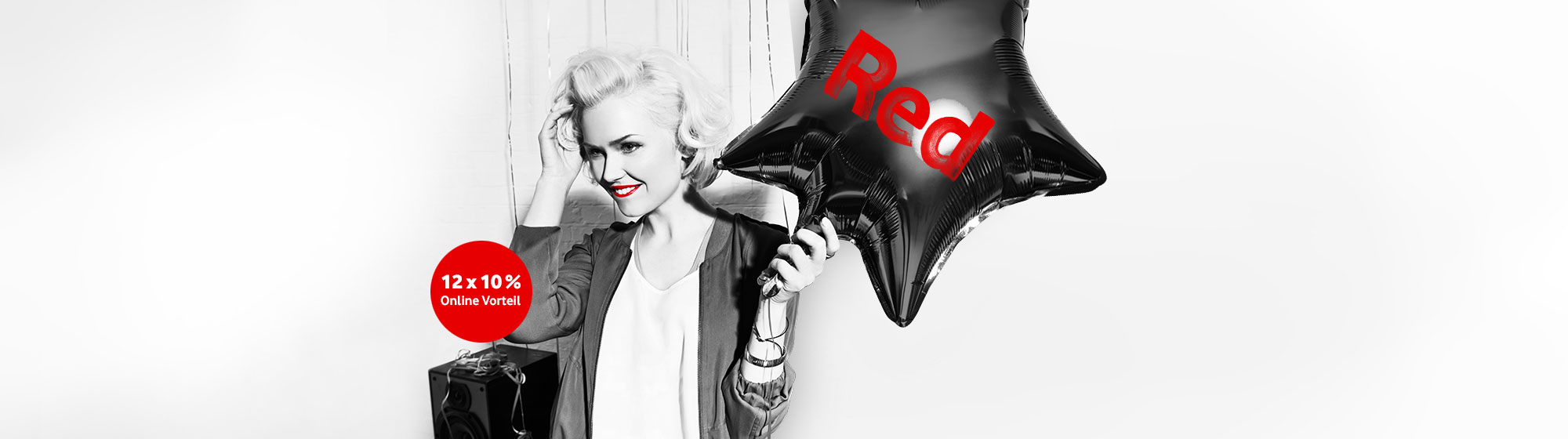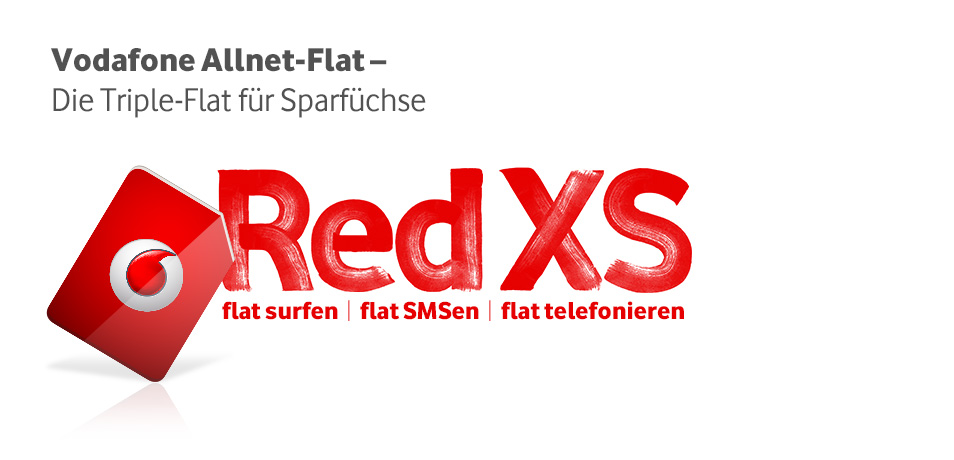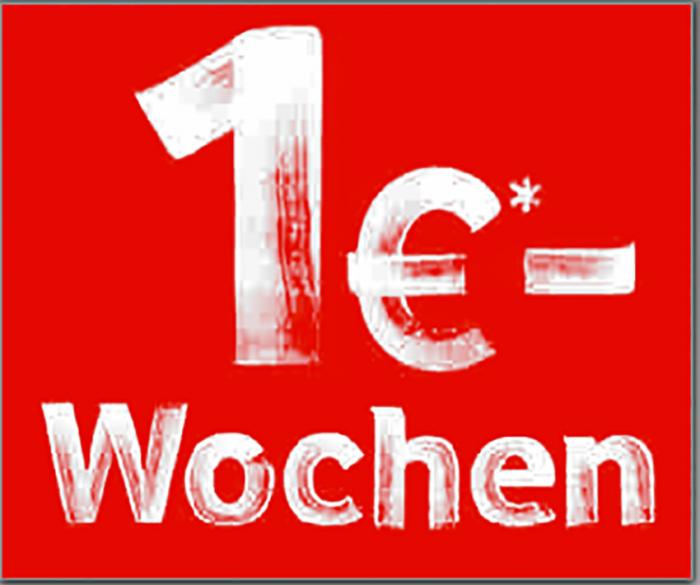
Wie heißt die Schrift von dieser Werbeanzeige?
gerade ist mir eine Handmade-Schriftart einer Webanzeige ins Auge gesprungen. Wisst ihr wie diese Schrift heißt?
vermutlich ist es einfacher, wenn Du die Anzeige mal verlinkst.
Aus dem Bauch raus, würde ich allerdings auf "handgemacht" tippen – zumindest der Kreidemarker-Effekt.
Das müsste aus der Vodafone-Werbung sein, also eher ein Font.
Ja, nachdem das Design nicht als Fließtext verwendet wird, könnten auch die Einzellogos RedXS usw. im Photoshop aus der Vodofone-Schrift erstellt worden sein. Klingt plausibel.
Dass es ein Font ist der auf der Hausschrift basiert ist wirklich gut möglich. Danke für die Info. Ggf. suche ich mal nach einer ähnlichen Schrift.